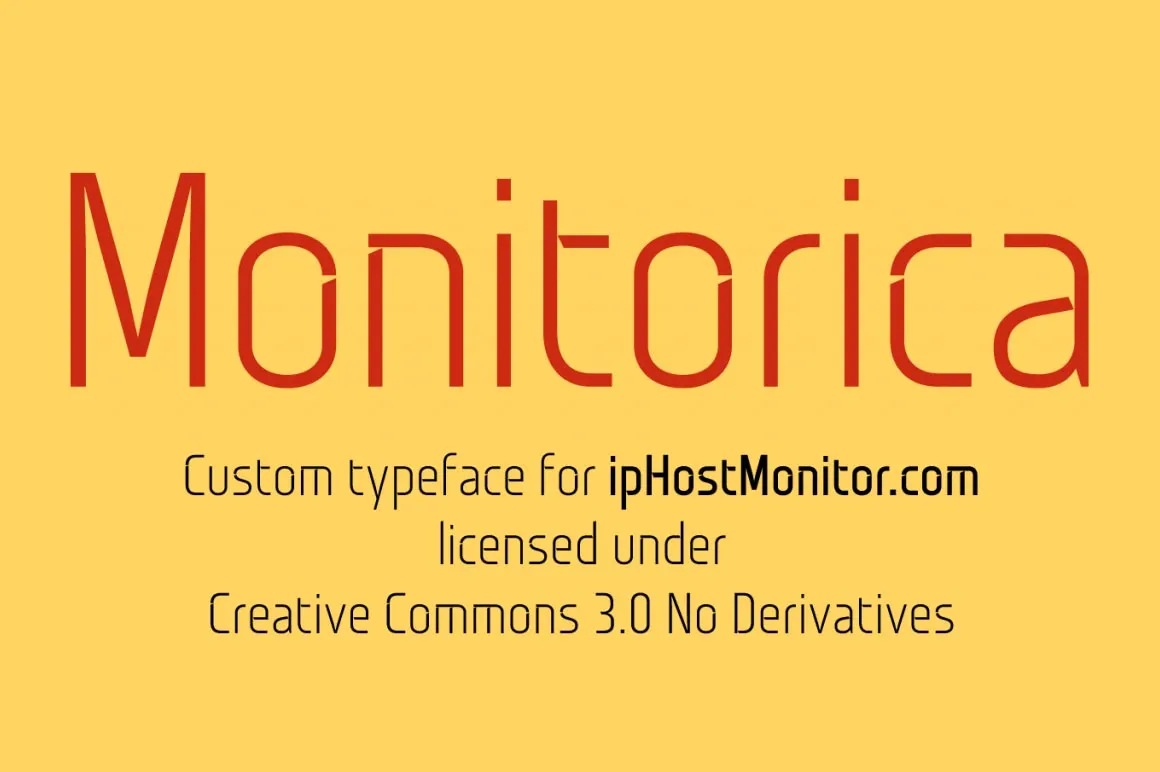
Monitorica Font é uma elegante tipografia de display criada pelo designer Hamilton que traz a essência de um estilo moderno e limpo para seus projetos digitais. Inspirado na paleta de Sergiy Tkachenko, essa fonte destaca-se pela sua simplicidade e sofisticação, oferecendo uma maneira inovadora e funcional de personalizar textos em aplicativos online ou impressões digitais. Seja você um designer gráfico profissional ou um amante da arte digital, Monitorica Font é perfeito para aqueles que buscam um equilíbrio entre elegância e simplicidade na hora de criar trabalhos visuais incríveis. Descarregue a fonte e desfrute do seu visual único e limpo, sem comprometer o resultado final da sua arte digital.